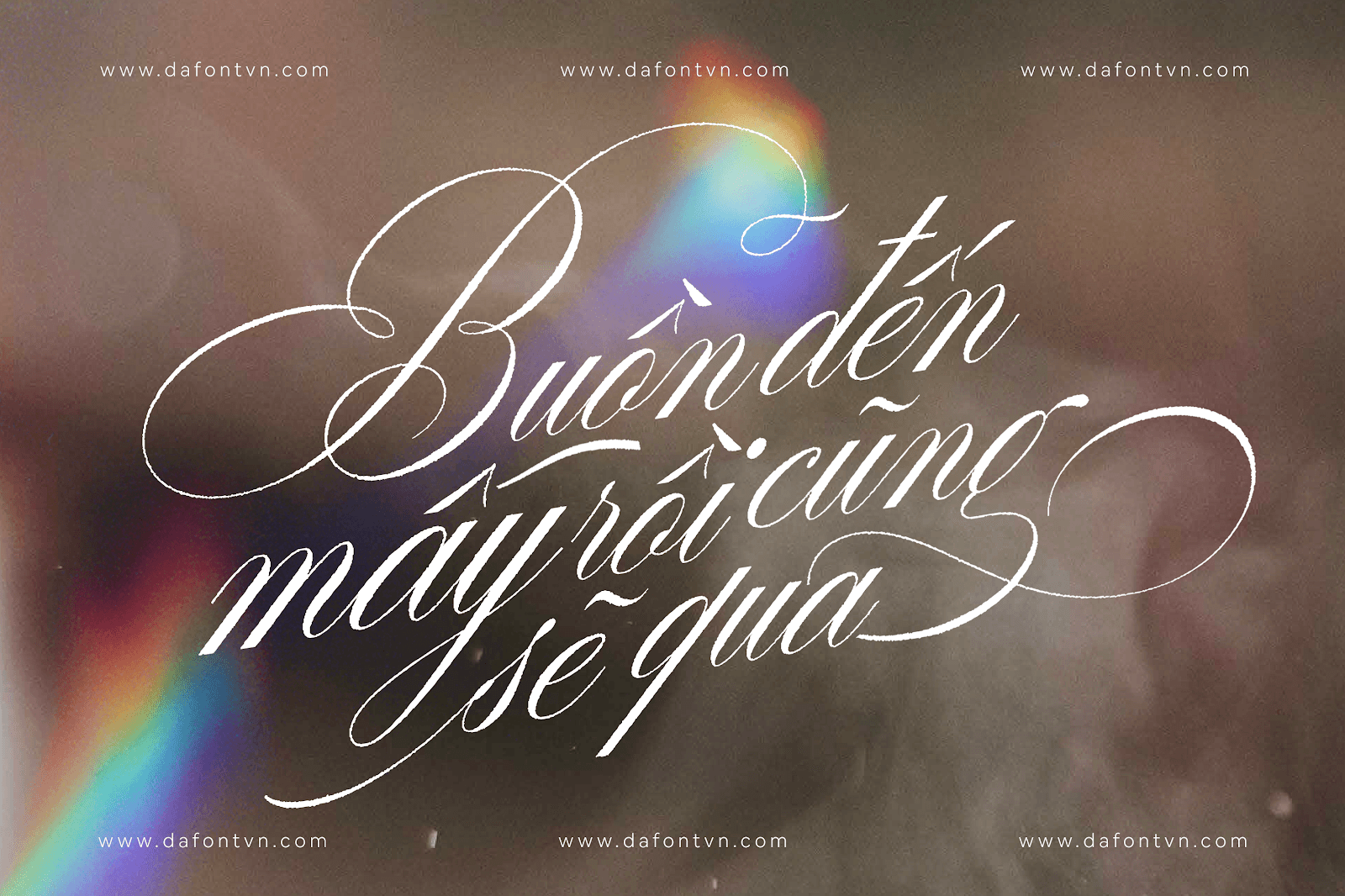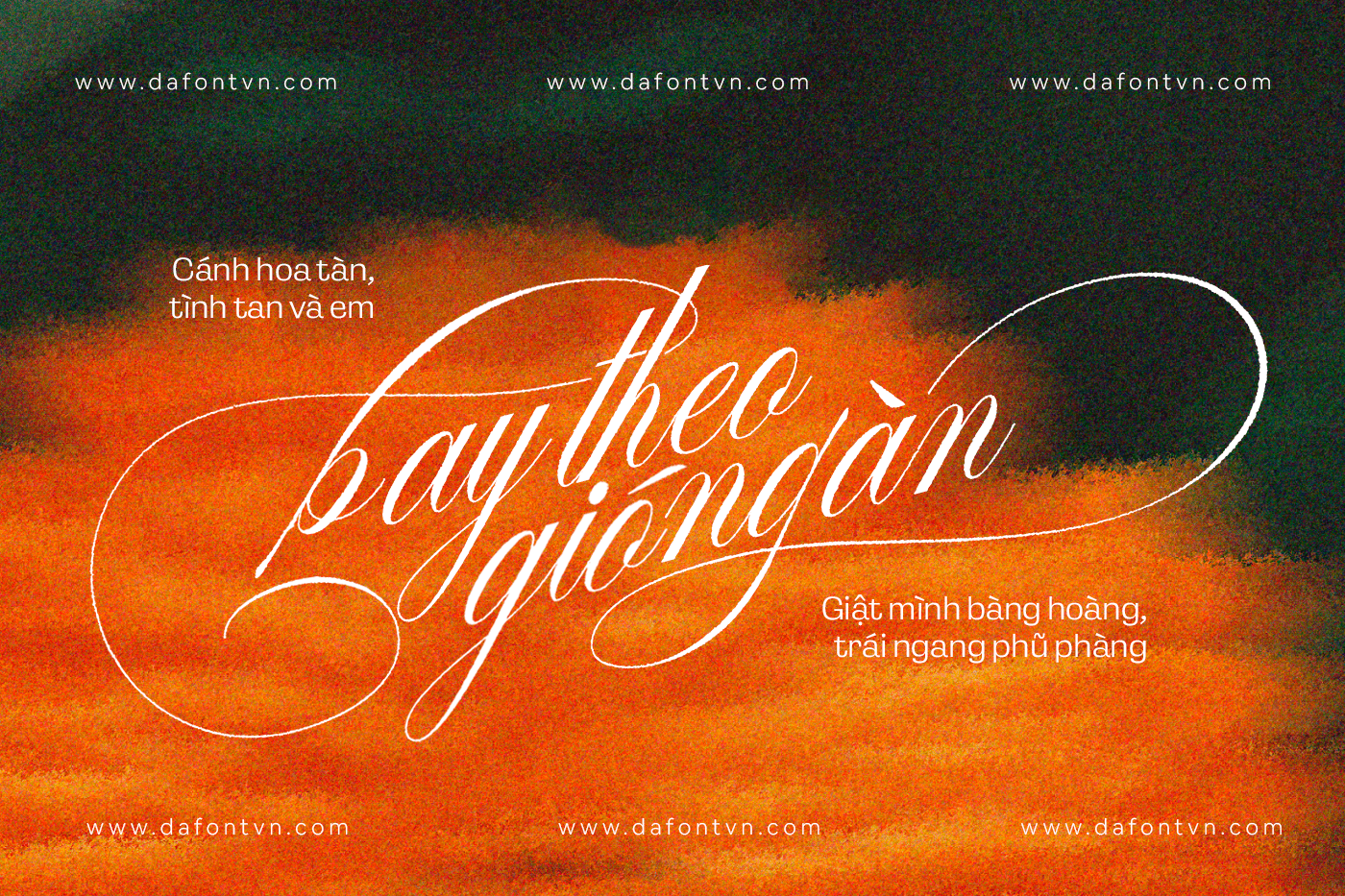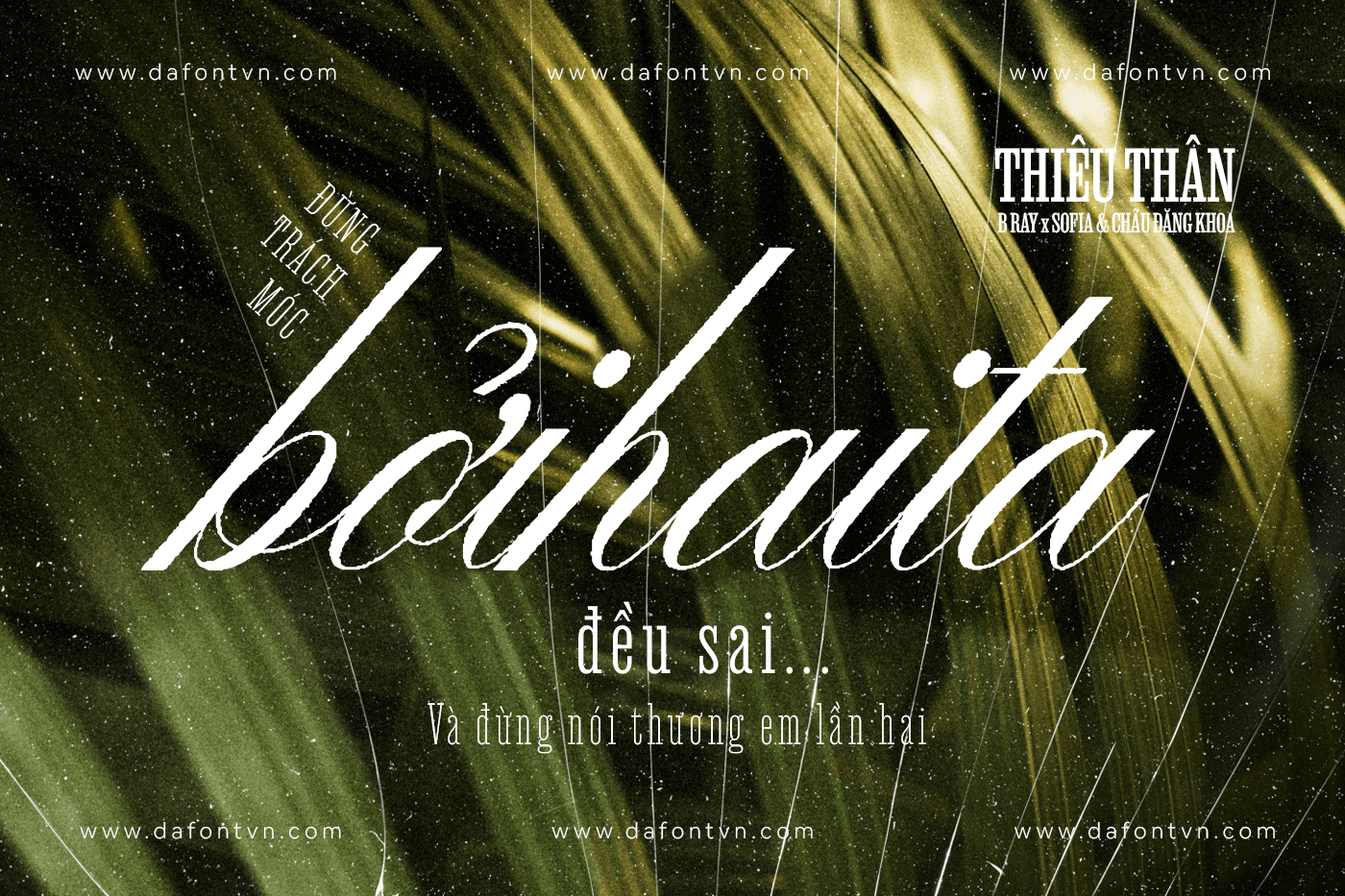
Desirable Brush Texture là font chữ với phiên bản bút lông với các nét được thiết kế mang phong cách cổ điển, lấy cảm hứng từ chữ viết tay của phụ nữ Ý và các bản thảo cổ.
Mặc dù bộ font này có 2 kiểu bao gồm 1 kiểu sans và 1 kiểu script, mình chỉ việt hóa 1 kiểu script này thôi, tuy nhiên bạn có thể dề dàng phối hợp với bất kỳ font chữ nào khác để tạo ra sự hài hòa với nhau.
Desirable Brush Texture hoàn hảo cho rất nhiều thiết khác nhau như thiệp đám cưới, bìa sách, thiệp chúc mừng, logo, nhãn hiệu, danh thiếp, poster hoặc ngay cả đối với bất kỳ công việc thiết kế nào đòi hỏi sự cổ điển, trang trọng hoặc xa hoa.
Đặc biệt font còn bao gồm hơn 600 glyph tuyệt đẹp cho cả chữ hoa và chữ thường, hãy dùng thử Desirable Brush Texture, tận hưởng sự phong phú của các tính năng và sự tinh tế của nó sẽ khiến bạn hài lòng và nâng cao khả năng sáng tạo của bạn!